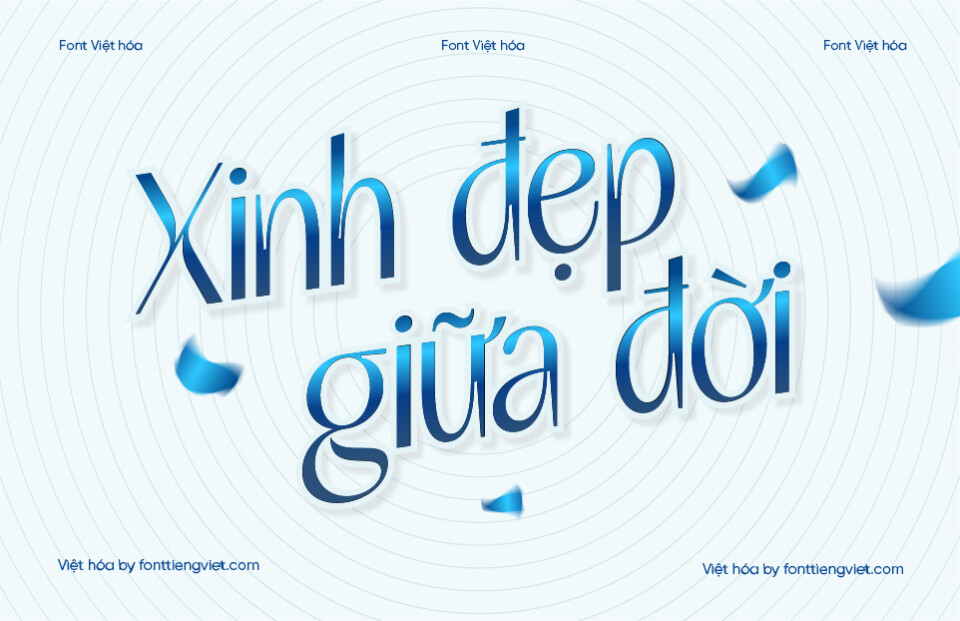
Font Việt hóa 1FTV VIP Gregonia
Giới thiệu về Font Việt hóa 1FTV VIP Gregonia
Trong thế giới đồ họa hiện đại, việc lựa chọn một bộ Font Miễn Phí chất lượng luôn là ưu tiên hàng đầu của các nhà thiết kế. Đặc biệt, Font Việt hóa 1FTV VIP Gregonia nổi lên như một hiện tượng nhờ sự kết hợp hoàn hảo giữa nét cổ điển và hơi thở đương đại. Đây là bộ font chữ thuộc phân khúc cao cấp, được đội ngũ 1FTV tinh chỉnh và việt hóa kỹ lưỡng để phục vụ cộng đồng designer tại Việt Nam. Với các đường nét thanh mảnh nhưng không kém phần mạnh mẽ, Gregonia mang lại cảm giác chuyên nghiệp cho mọi ấn phẩm truyền thông từ poster, logo đến các bìa tạp chí nghệ thuật.
Đặc điểm nổi bật của Font Việt hóa 1FTV VIP Gregonia
Điều làm nên sức hút của Font Việt hóa 1FTV VIP Gregonia chính là hệ thống ký tự được thiết kế tỉ mỉ với độ tương phản cao. Các nét chữ có sự biến chuyển linh hoạt giữa dày và mỏng, tạo nên một nhịp điệu thị giác vô cùng lôi cuốn. Khi áp dụng vào tiếng Việt, các dấu thanh được đặt ở vị trí tối ưu, không gây cảm giác rời rạc hay mất cân đối như nhiều bộ font ngoại nhập khác. Khả năng hiển thị sắc nét trên cả màn hình kỹ thuật số lẫn bản in giúp bộ font này trở thành công cụ đắc lực cho những ai đang tìm kiếm sự khác biệt và đẳng cấp trong tác phẩm của mình.
Ứng dụng thực tế của bộ font trong đời sống
Font Việt hóa 1FTV VIP Gregonia không chỉ giới hạn trong lĩnh vực quảng cáo mà còn lan tỏa mạnh mẽ vào môi trường giáo dục và đời sống. Các em học sinh và thầy cô có thể sử dụng font chữ này để thiết kế những slide bài giảng sinh động hoặc làm tiêu đề cho các báo tường, tập san nhà trường. Sự rõ ràng của Gregonia giúp người xem dễ dàng tiếp nhận thông tin, đồng thời kích thích tư duy thẩm mỹ của các bạn trẻ ngay từ khi còn ngồi trên ghế nhà trường. Đối với các doanh nghiệp, đây là lựa chọn tuyệt vời cho bộ nhận diện thương hiệu, giúp khẳng định vị thế và sự uy tín thông qua từng con chữ.
Lý do bạn nên sở hữu Font Việt hóa 1FTV VIP Gregonia ngay hôm nay